Font Việt hóa Hoài cổ đẹp cho thiết kế
Font Việt hóa Hoài cổ mang phong cách retro, cổ điển đầy hoài niệm, giúp thiết kế của bạn trở nên ấn tượng và độc đáo hơn. Đây là lựa chọn lý tưởng cho poster, typography, bìa sách, hay các dự án sáng tạo cần nét đẹp xưa cũ nhưng vẫn tinh tế.
Font Việt hóa TF Quartus
TF Quartus Việt hóa là một font chữ nổi bật với thiết kế vintage, mạnh mẽ và cứng cáp, gợi cảm giác về những bảng hiệu cũ kỹ, quảng cáo công nghiệp thời xưa hoặc các ấn phẩm mang phong cách hoài cổ đầy nam tính. Font này toát lên vẻ vững chãi, bền bỉ và đầy cá tính, lý tưởng để tạo điểm nhấn độc đáo và thu hút mọi ánh nhìn trong các thiết kế đòi hỏi sự mạnh mẽ và phong cách riêng biệt.
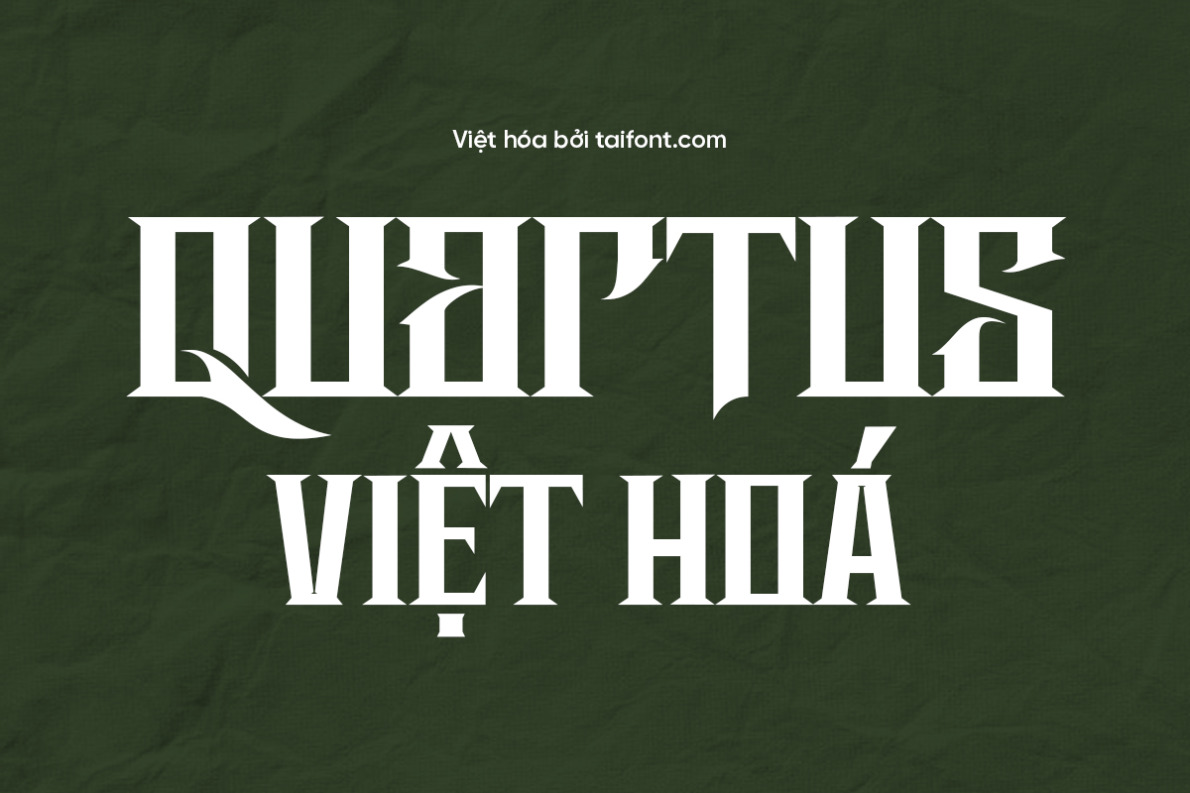
Font Việt hóa TF Dragonit
TF Dragonit Việt hóa là một font chữ trang trí nổi bật với thiết kế mạnh mẽ, sắc nét và đầy kịch tính, gợi cảm giác về những trận chiến sử thi, thế giới giả tưởng và những câu chuyện về rồng. Font này toát lên vẻ oai phong, bí ẩn và đầy quyền lực, lý tưởng để tạo điểm nhấn độc đáo và thu hút mọi ánh nhìn, đặc biệt trong các thiết kế liên quan đến game.
Font Việt hóa TF Olyphs
TF Olyphs Việt hóa là một font chữ trang trí nổi bật với thiết kế sắc nét, to đậm và đầy ấn tượng. Font này mang đến vẻ ngoài mạnh mẽ, dứt khoát và mang phong cách cổ điển, gợi cảm giác về những bảng hiệu cũ kỹ, quảng cáo thời xưa hay những dòng chữ được in ấn một cách dứt khoát. Olyphs toát lên vẻ vững chãi, bền bỉ và đầy cá tính, lý tưởng để tạo điểm nhấn độc đáo và thu hút mọi ánh nhìn trong các thiết kế đòi hỏi sự mạnh mẽ và hoài niệm.
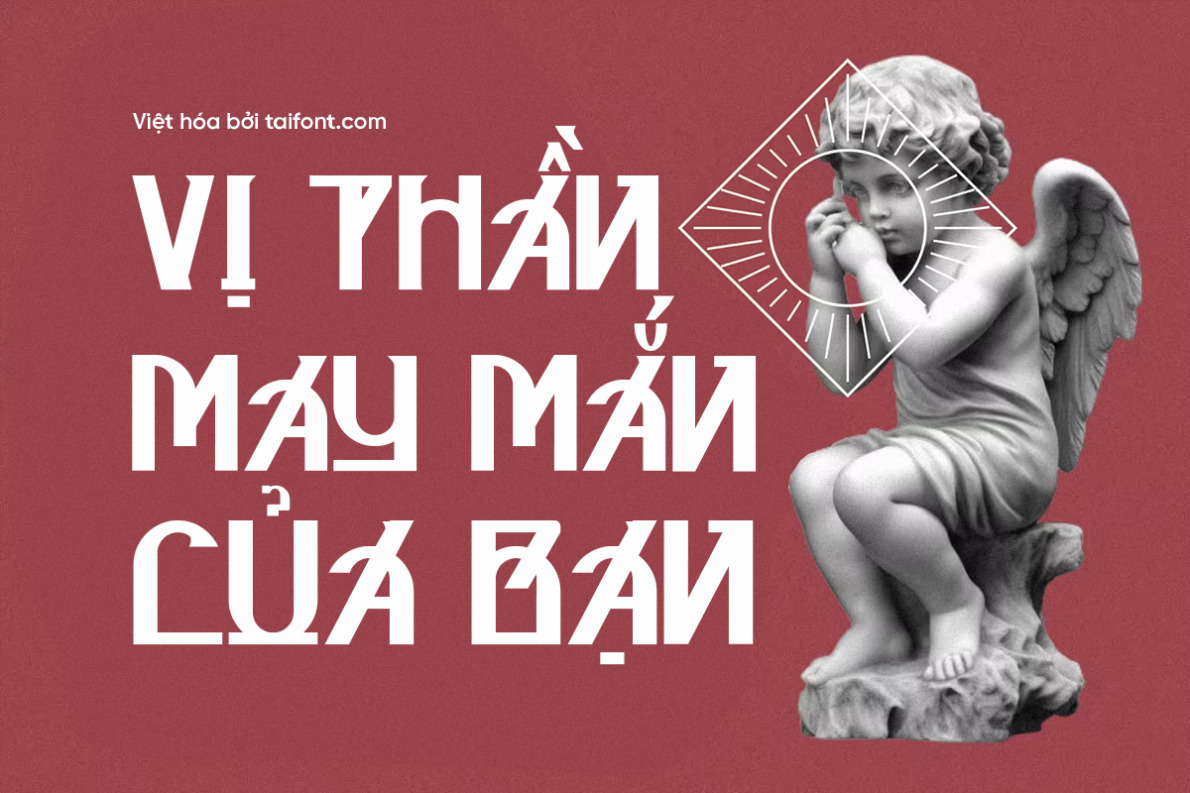
Font Việt hóa TF Lovante
TF Lovante Việt hóa là một font chữ nổi bật với thiết kế mang đậm phong cách vintage, cổ điển và đầy phong trần, lý tưởng để tái hiện vẻ đẹp xưa cũ, mạnh mẽ nhưng vẫn rất nghệ thuật. Font này toát lên sự vững chãi, uy nghi và một chút bụi bặm của thời gian, gợi nhớ về những bảng hiệu vẽ tay của các cửa tiệm truyền thống.
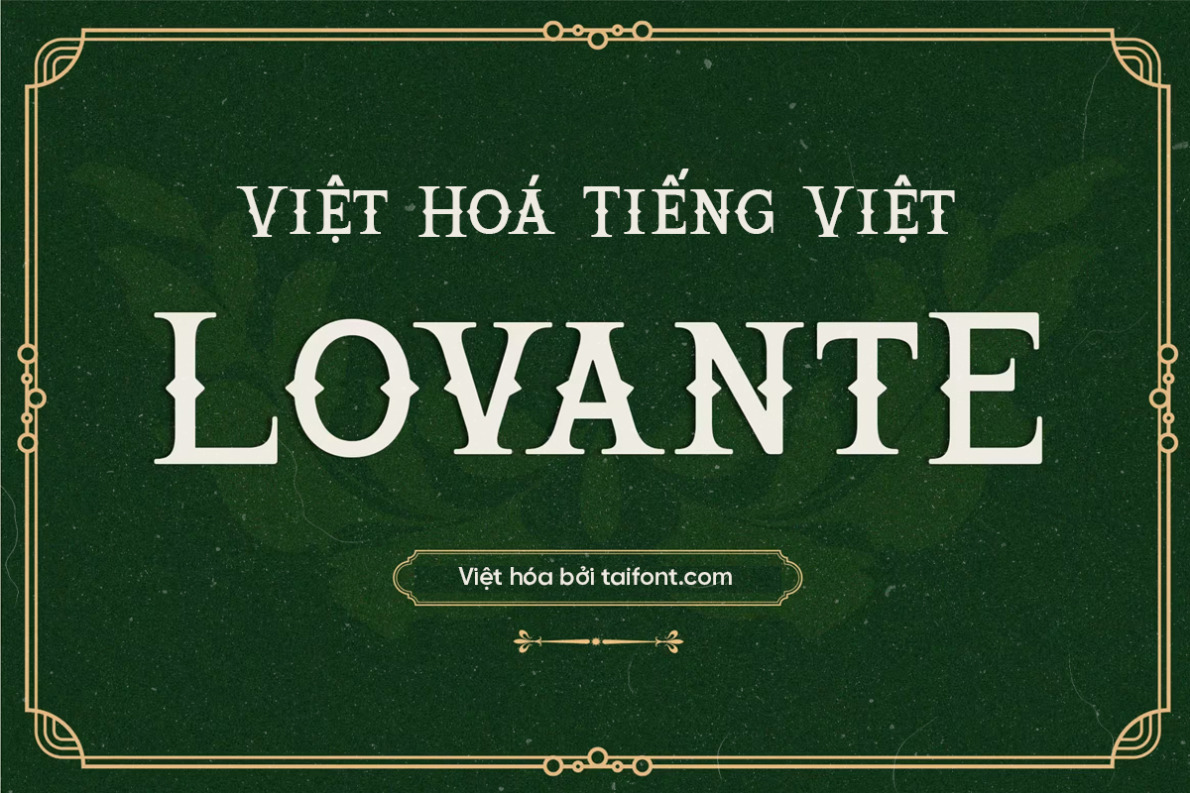
Font Việt hóa TF Estocrat
TF Estocrat Việt hóa là một font chữ trang trí nổi bật với thiết kế mang đậm phong cách vintage, cổ điển và đầy quý phái. Font này toát lên vẻ đẹp của sự hoài niệm, tinh tế và một chút uy nghiêm, gợi nhớ về thời kỳ vàng son của nghệ thuật thủ công và in ấn xưa. Những đường nét của Estocrat thường được chăm chút tỉ mỉ, có độ dày vừa phải, mang lại cảm giác vững chãi và đáng tin cậy.